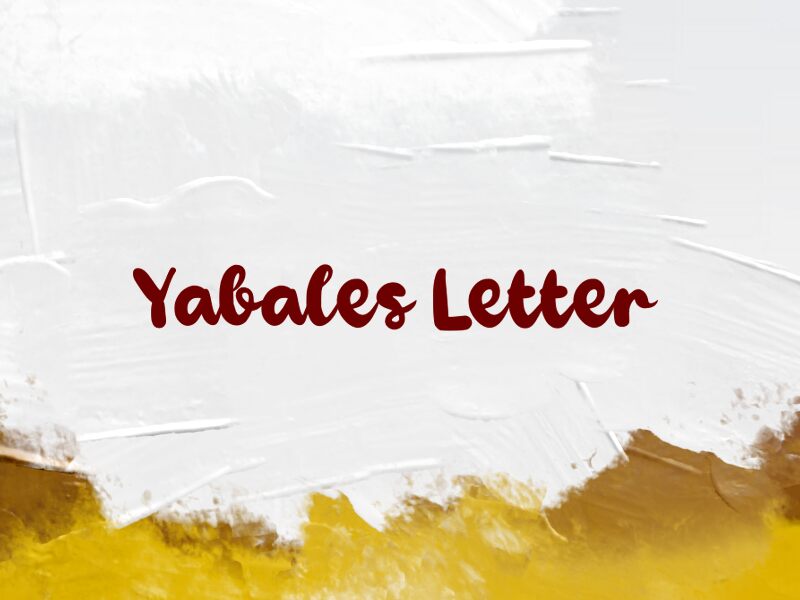
Yabales Letter
Yabales Letter od Wep je bezplatné brush písmo s velkými zaoblenými tahy a vysokými smyčkami, které mu dodávají živý, ručně psaný rytmus. Široké, plné tvary působí měkce a přirozeně, zatímco opakující se smyčky u horních dotahů a nízká, plynulá napojení propůjčují písmu ležérní a výrazný charakter.
Díky tomuto náboji krátké texty skvěle vyniknou na logách kaváren, etiketách produktů, samolepkách, příspěvcích na sociálních sítích nebo veselých obalech. Písmo se také skvěle hodí na přáníčka a citáty v titulcích, kde plné křivky a vysoké smyčky udrží pozornost v layoutu i bez další dekorace.